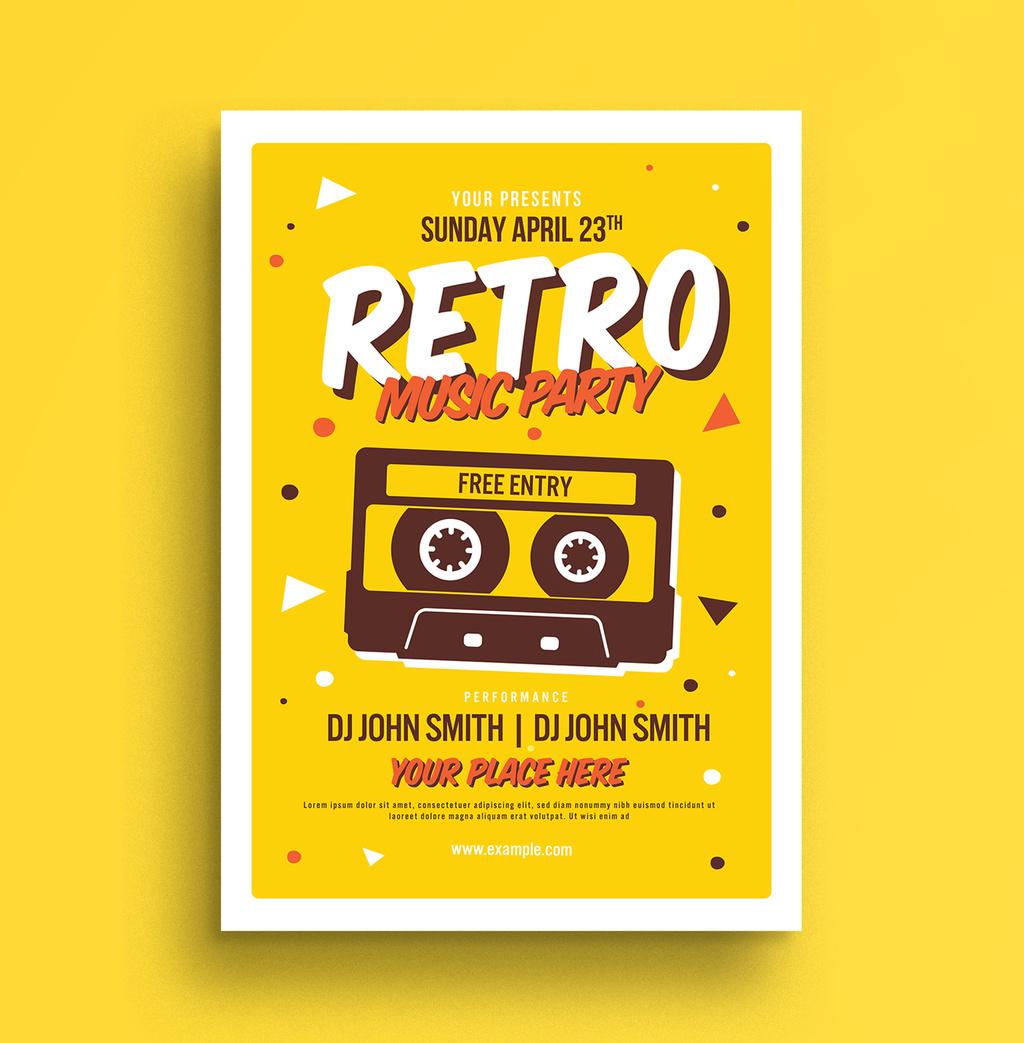
Suche den Schriftnamen für Retro Music Party
Das ist doch eine ganz bekannte Schriftart, oder nicht? Kennt jemand von euch den Namen oder eine ähnliche kostenfreie Schriftart ("Retro Music Party/Your Place Here"). Leider weiß ich nicht mehr, woher dieses Bild stammt. Wahrscheinlich aber Behance oder Dribbble.
Zur Marker- bzw. Pinselschrift fällte mit die sehr ähnliche Flash Bold ein:
Wie wäre es damit: House Slant
Designer: House Industries
Year: 1999
Publisher: House Industries
No lower-case or accented characters.
Die Serifenlose in All Caps könnte die Bebas Neue und auf dem Kassettenlabel die Bebas Kai (Bebas) sein ...
Typeface:	Bebas Kai
Designer:	Ryoichi Tsunekawa
Publisher:	Flat-IT
Year:		2014
Note of the author
Updated Bebas Original http://www.dafont.com/bebas.font
Along with Bebas Neue, Bebas Kai is improved version of
Bebas Original.
Und DJ John Smith ist noch mal eine andere Schrift ... https://www.fontsquirrel.com/fonts/oswald ?